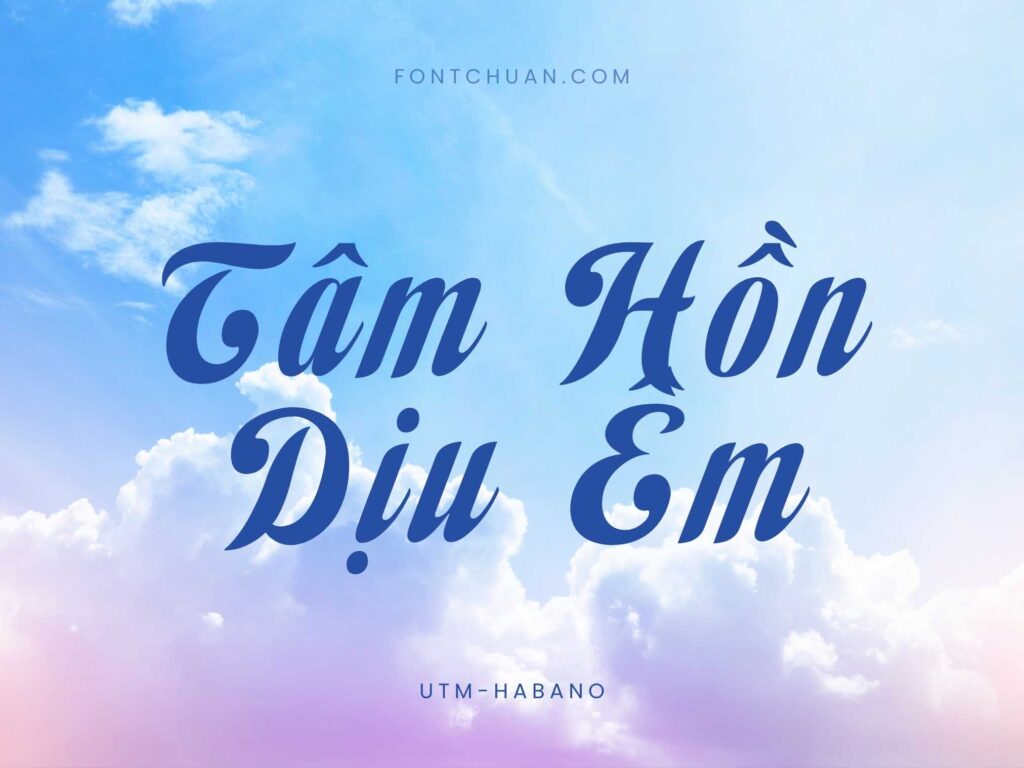
Font UTM Habano Việt Hóa
UTM Habano là một font chữ mang phong cách cổ điển và sang trọng, lấy cảm hứng từ các thiết kế typography vintage của thế kỷ 20. Font này sở hữu nét chữ mềm mại, đường cong uyển chuyển và độ tương phản cao, phù hợp với những thiết kế đòi hỏi sự tinh tế và nghệ thuật. Font đã được Việt hóa bởi Thiên Minh, hỗ trợ đầy đủ tiếng Việt cùng hơn 200 ngôn ngữ khác, giúp mở rộng khả năng sử dụng. Thành viên của Font Chuẩn đã sưu tầm và giới thiệu font này nhằm đáp ứng nhu cầu bạn đọc, cung cấp nguồn tham khảo chất lượng và ứng dụng thực tế vào các dự án thiết kế
Về đặc điểm thiết kế, UTM Habano có các đường nét thanh lịch, độ cong tinh tế và mang hơi hướng cổ điển. Font này phù hợp với nhiều ứng dụng như thiết kế logo, bao bì sản phẩm, biển hiệu, thiệp mời và các dự án sáng tạo. Các ngành nghề như quảng cáo, ẩm thực, thiệp cưới và giáo dục có thể tận dụng font này để tạo nên sự khác biệt và thu hút trong các ấn phẩm thiết kế